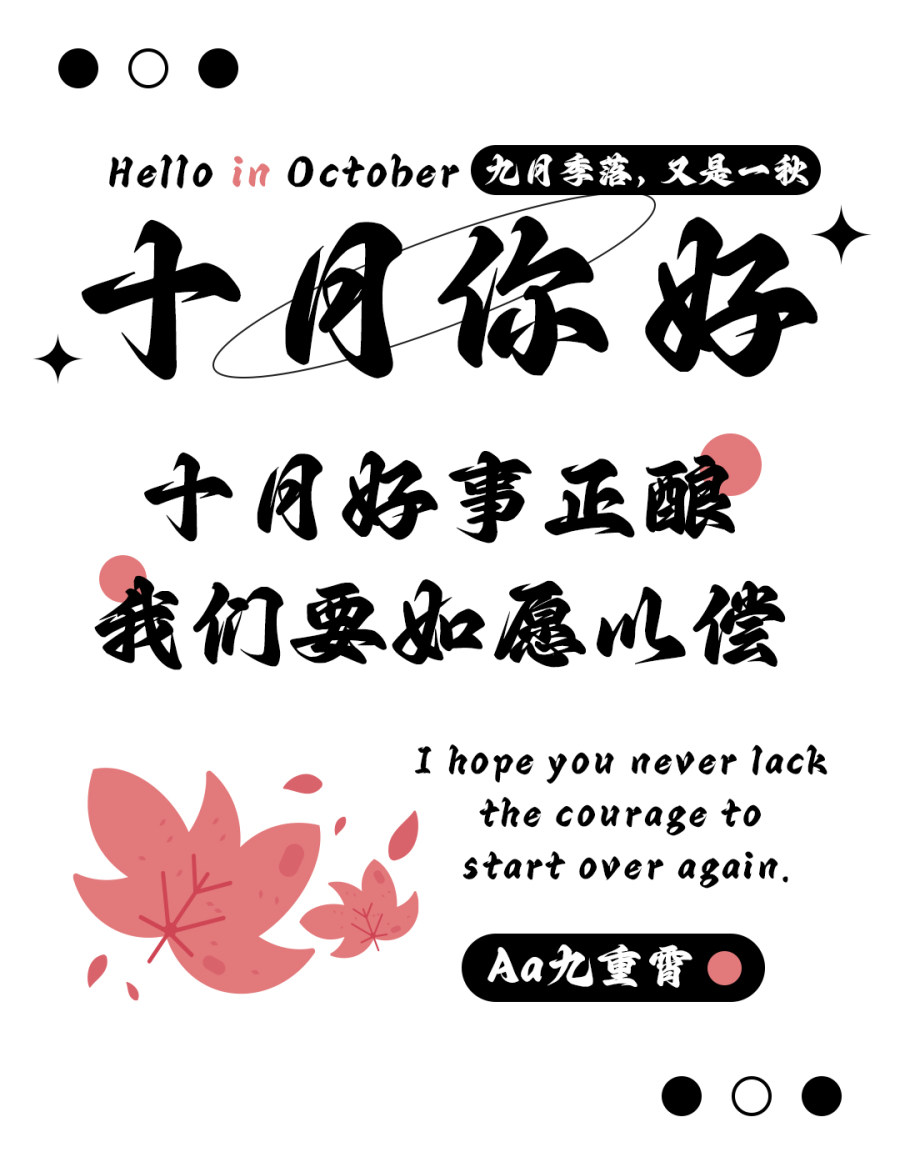
Aa九重霄——国潮手书字体的现代魅力
《Aa九重霄》以行楷为基础,结合iPad手写技术,通过数字笔刷的巧妙运用,呈现出一种独具魅力的手书字体。其笔画流畅而有力,仿佛祥云聚散,轻盈地飘逸在纸上。这种戏剧性的轻重变化不仅增添了字体的视觉冲击力,还赋予了文字以生命力。
《Aa九重霄》成功捕捉到了国潮风范,将古今的字形美感巧妙融合。字体的线条流动感强烈,给人一种时光穿越的错觉,仿佛能听到历史的呼吸声。这款字体不仅令人陶醉于其独特之美,也彰显了现代手写艺术的潜力。它是一种时尚的表达方式,将传统与现代相互交融,为文字赋予了更深层次的意义。
字库品牌: Aa字库